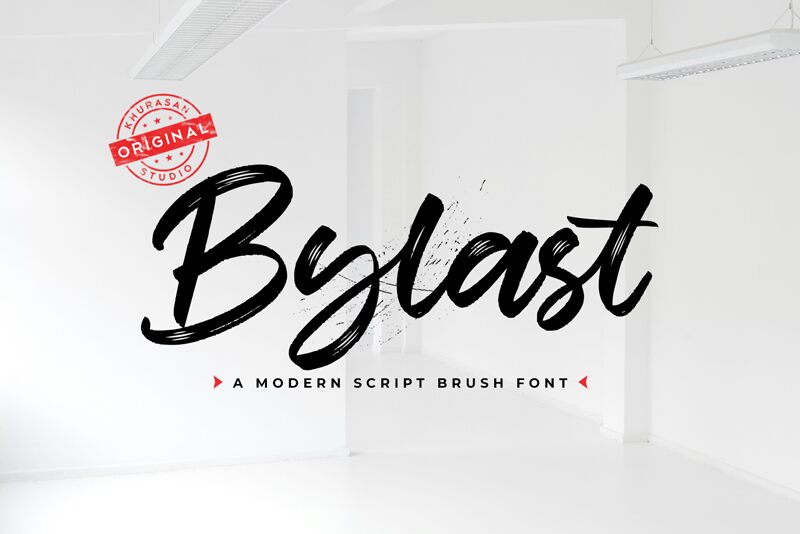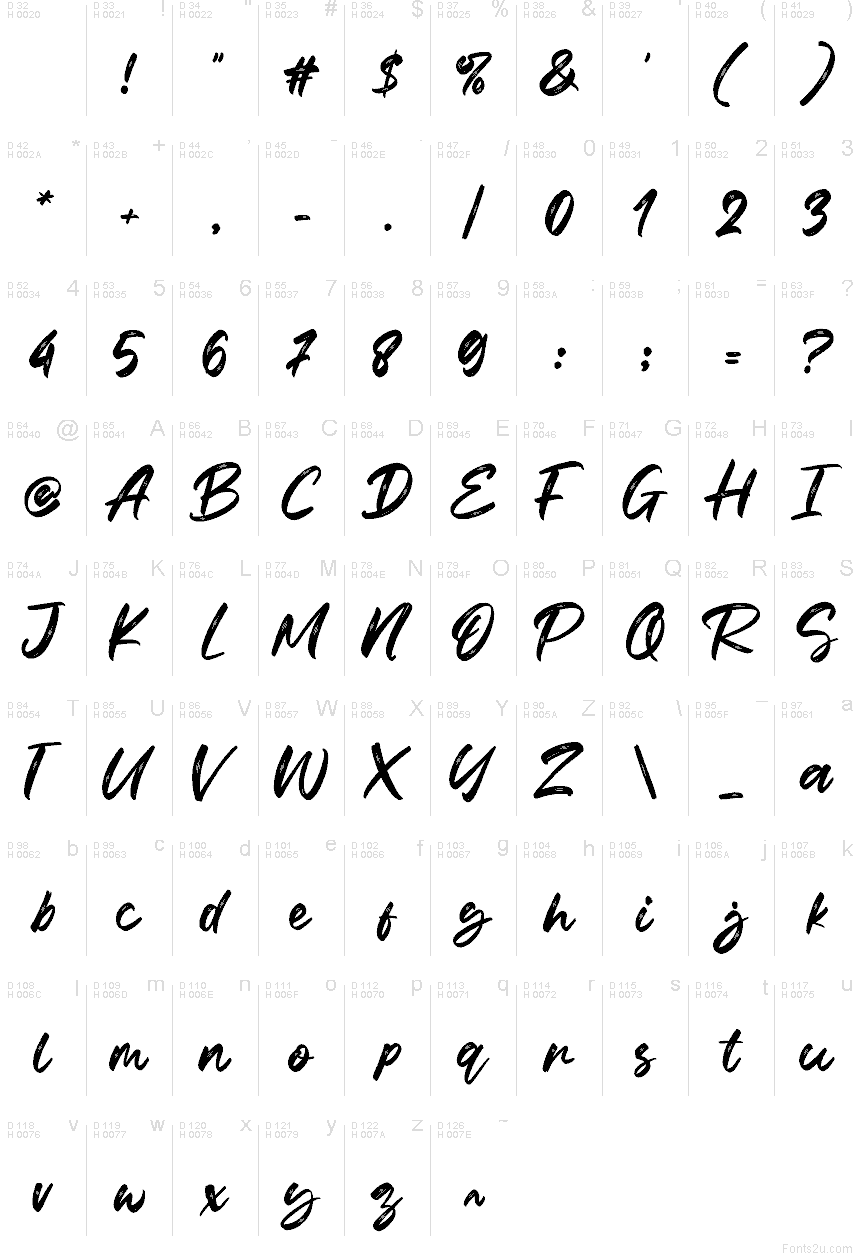
Bylast من Khurasan هو خط مجاني بأسلوب الفرشاة، يتميز بضربات سريعة وانسيابية وإيقاع كتابة يدوي عفوي. تتحرك الحروف في أقواس طويلة وانحناءات رشيقة، مما يمنحها طابع التوقيع السريع بدلاً من الخطوط المنسقة بدقة.
تعد هذه الحيوية مثالية لمسودات الشعارات، وتغليف منتجات التجميل، وعناوين وسائل التواصل الاجتماعي، وهوية المقاهي، وعناوين الملصقات، حيث تكون اللمسة الشخصية أكثر أهمية من الدقة الرسمية. تبرز العبارات القصيرة جمال هذا الخط، إذ تمنح الضربات البداية العريضة والوصلات الانسيابية لكل سطر حضوراً واثقاً كأنه مرسوم باليد، مما يثري التصميم دون الحاجة إلى زخارف إضافية.
Bylast